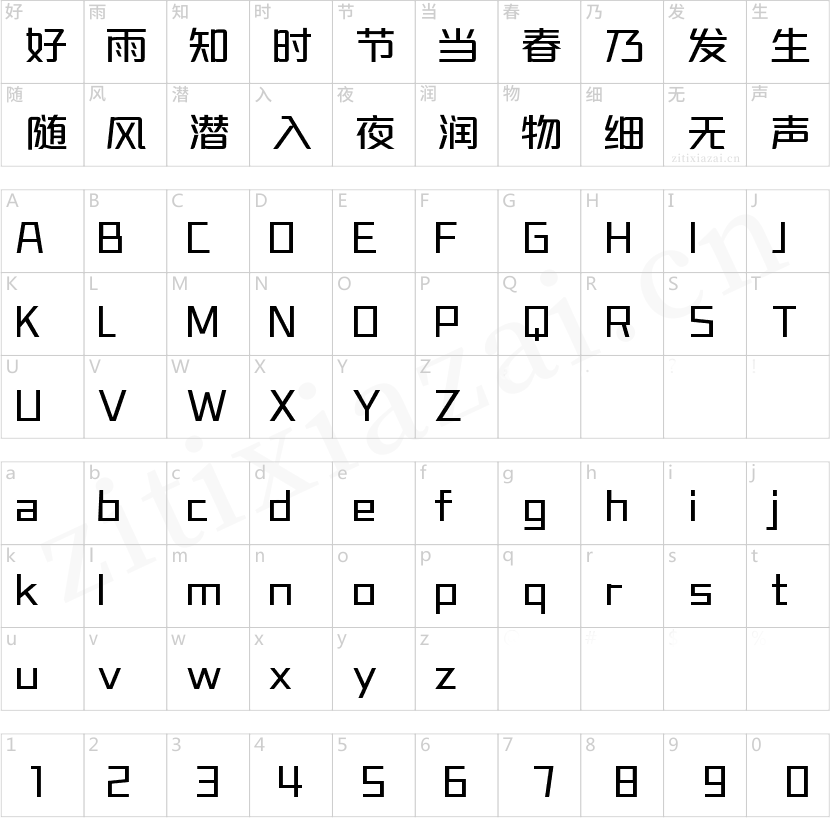
字魂宇宙巡航体
字魂宇宙巡航体,这款字体结构工整、笔画清晰,兼顾美观与易读性,适用于标题、正文、海报、包装、LOGO 等多种场景。字形优雅稳定,风格百搭耐看,适配日常排版与创意设计,让文字呈现更舒适、更具质感。字魂宇宙巡航体一笔一画,皆是细节,以均衡的比例、流畅的线条打造舒适视觉体验,字形端正大气,风格简约现代。无论是商业设计、品牌宣传还是日常排版,都能轻松驾驭,让文字更有格调与力量。字魂宇宙巡航体字体下载。
字魂字体字魂宇宙巡航体字体是由字魂创意字库设计并生产的一款可商用的字体,共8字重,被收录于字魂先锋系列。该字体支持GB-2312标准以及最新的字魂ZH7144标准,包含7144个中文、字母、符号和数字,字体类型偏向黑体,具有简约、时尚的风格,在市面上广泛用于海报企宣、视频综艺、党政公务等场景。